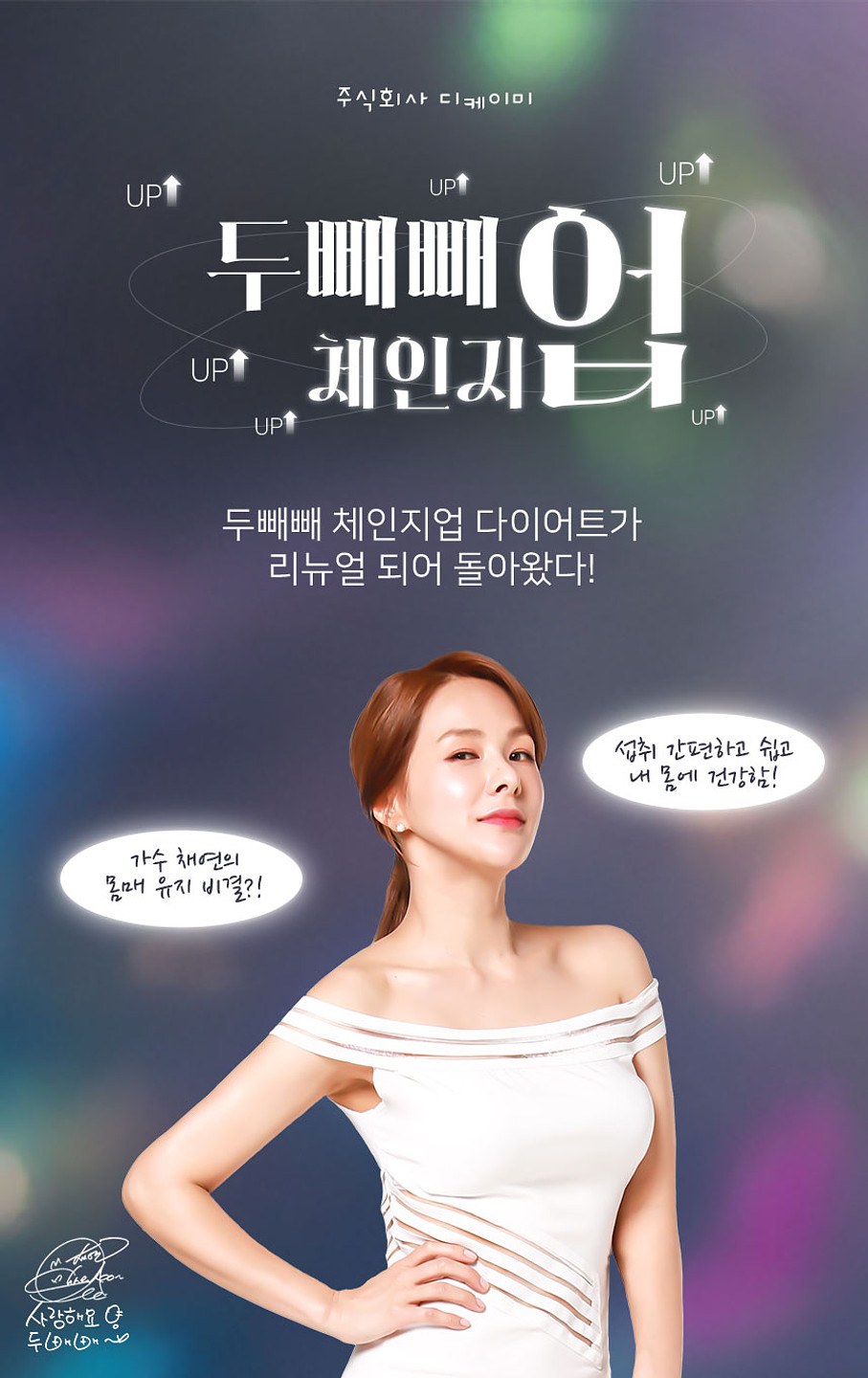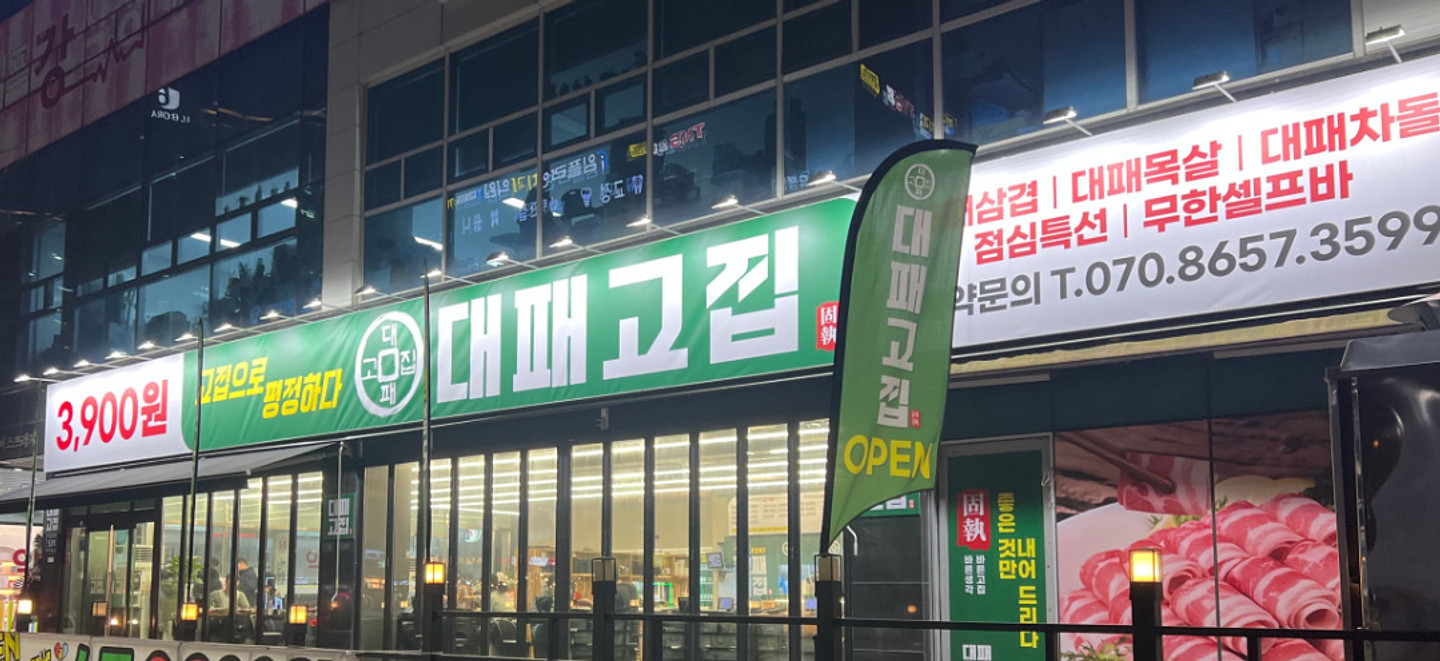
이 폰트 아시는 분 계신가요?ㅜ
혹시 이 폰트 무슨 폰트일까요?
이 폰트 무엇일까요?
HS산토끼체 말고 다른 서체가 사용된 거 같은데 어떤 폰트를 사용한 걸까요?
재활용마크에 사용된 폰트는 뭔가요?
혹시 이 영어폰트 찾을 수 있을까요??ㅜㅜ 적어도 비슷한 폰트라도 있으면 알려주시면 감사하겠습니다ㅜㅜㅜㅠ
이 서체가 뭔지 궁금합니다
좌상단 이별마저도 사랑이다-김이현 무슨 폰트일까요 ??
카카오톡 기본 서체였습니다. 연애일기, 모던명조로 추정됩니다. 갑자기 폰트가 사라져서 당황하는 중입니다.
혹시 이 카톡폰트 이름 뭔지 알 수 있을까요? ㅠㅠ 글씨체 설정보다가 실수로 눌렀는데 찾을 수가 없습니다…
이거 폰트가 뭘까요ㅠㅠㅠ
이 폰트 뭘까요 ㅠ ㅠ 무료폰트 같긴한데
무슨 폰트인지 알려주세요 제발요 첫 질문입니다 !
요 폰트가 뭔지 궁금합니다 ㅠ 아시는 분 계실까요`?
무슨폰트인가요
오다다 사이트 로고입니다. 폰트 이름을 알고 싶어요~
이 폰트 이름 알고 싶어요ㅜㅜ 비슷한 폰트라도 알려주시면 감사합니다
이 폰트 뭘까요 ㅠ
혹시 무슨 폰트인지 아시는 고수님 계실까요??;;
한글 영어 무슨폰트일까요? 미리감사합니다.
여기어때 잘난체를 닮았는데 무슨서체인지 모르겠어요
요거 폰트가 뭔지 알려주실분ㅠㅠㅜ
이 폰트 아시는부운~~~ 미리 감사합니다🙇🏻♀️
DS 팡팡이랑 비슷하게생긴 폰트있나용??
간판글씨체뭔지아시나요?
이 폰트 이름이 뭘까요..? 검색해도 안나오네요 ㅠㅠ
무슨폰트인지알고싶숨다…
이거 무슨 폰트일까요ㅠㅠ?
폰트 뭐야
이거 폰트 알 수 있을까요?,, 막 거칠게 색이 벗겨진 듯한 질감은 직접 넣으신 듯 하거든요.. 안에 별무늬 파랑색두 직접 넣으신 것 같은데 폰트를 모르겠네요
TTIGothicR 이라고 되어있는데 혹시 어떤 폰트일까요..
VIBE와 비슷한 폰트가 궁ㅇ금합니다 ㅠ
무슨 폰트인지 아시는 분ㅠ
아제발제인생소원이에요제발이거무슨폰튼가요오오오오ㅗ오오,,,,,,,,,,,,,,,,,,,,,,,ㅠㅠㅜㅠㅜㅠㅜ
이 폰트는 무슨 폰트일까요?
보라색 글씨 혹시 어떤 폰트인가요??
네모 박스안에 있는 숫자와 글씨 폰트 어떤거 사용했는지 알 수 있을까요?
이렇게 일부 글자에 뒷배경으로 파스텔톤 색깔? 들어가는 폰트인데 어떤 폰트일까요? 안드로이드에요
유튜브 광고로 뜨는 무슨 게임에서 나오는 폰트인데 무슨 폰트일까요?
빨간색으로 "명덕식당"이라 써진 폰트가 궁금합니다.
폰트이름 알려주세용
폰트 뭔가요??
무슨 폰트인가여??
이 폰트 뭘까요???
자막 폰트 뭘까요?
이 폰트 아시는 분 계시면 한 번만 알려주세요!,
작업을 해야하는데... 일러 파일 글자가 다 깨져있어서 뭔 폰트인지 모르겠어요 HELP
이게 뭘까요?
위러브 - 주님 난 알고 싶어요. 유튜브에 나오는 가사입니다. 한글폰트 궁금합니다!
쥬라기치킨 부분 어떤 폰트일까요~? 간판하려고 하는데 너무 어렵습니다ㅠㅠㅠ
요로코롬 예쁜 폰트 이름이 멀까욤??^^~♡♡
폰트 궁금합니댜 ~~~~
시간 표기 폰트 뭘까윰
위 아래 두 개 폰트 뭘까요?